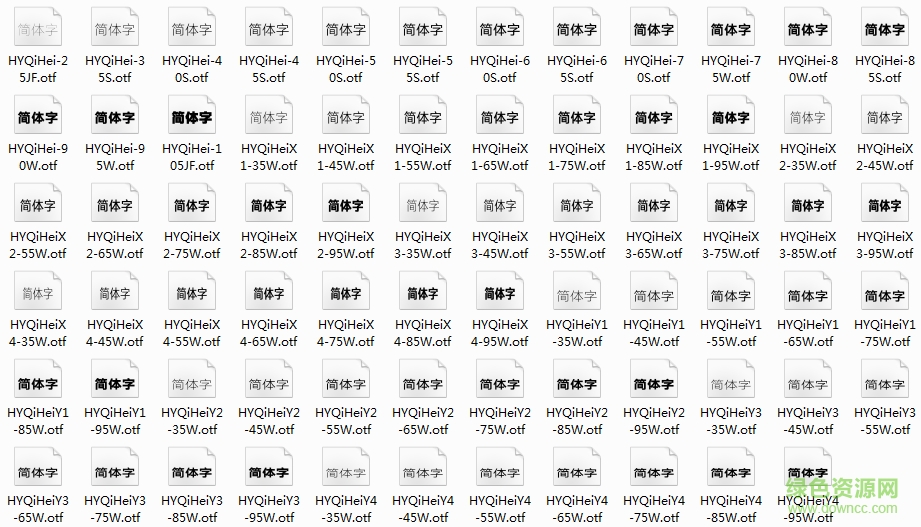
汉仪旗黑是由三个系列字体(长、方、扁)组成的一个庞大而完整的家族字体,从最细的25到最粗的105,共计15个字重,是迄今为止国内最大、最丰富的字重的家族字体,可以满足企业多渠道,全方位的内容设计以及定制化需求,实现企业品牌形象在各渠道的统一呈现。
笔画设计
设计简约、爽朗富有时代气息固然重要,但我们在设计时不能忘却字的民族性和传统文化,笔划必须要有内涵。
笔画设计中融入了书写的韵味,采用“阴阳线”的处理方法,讲究线条之美,使笔划挺拔有力,刚柔相济。
通过笔画的粗细变化,赋予字体不同的性格与表现力,但“骨子里”却是“一家人”,线条劲道,紧致。
结构设计
UD设计尽可能减少多余的修饰元素,将除字形识别以外的信息量将至最低,尽可能避免过大的弧度为阅读所带来的不稳定感,更方便视觉障碍者的阅读。
西文设计
汉仪旗黑的西文设计沿用了与著名字体helvetica和Univers相同的Neo-grotesque字形风格。Neo-grotesque类字形简洁匀质硬朗,可以与旗黑的中文部分达成非常良好的配合。
命名方式
汉仪旗黑作为一款家族字,创新性地运用了西方字体系统化字库的使用和命名方式,使设计师字体选择的过程更轻松便捷